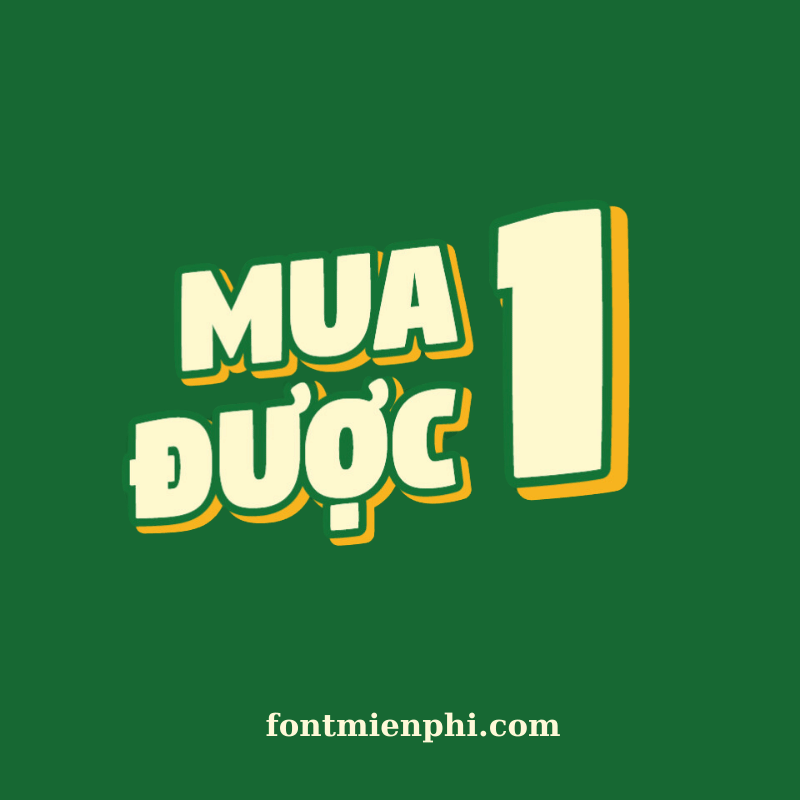
Font Việt hóa 1FTV VIP Digitalt
• Tác giả:  gluk
• Việt hóa:  fonttiengviet.com
Trong thế giới thiết kế đồ họa hiện đại, việc lựa chọn một bộ phông chữ phù hợp đóng vai trò quyết định đến tính thẩm mỹ và sự chuyên nghiệp của sản phẩm. Một trong những lựa chọn hàng đầu hiện nay chính là Font Việt hóa 1FTV VIP Digitalt. Đây là bộ Font Miễn Phí được tinh chỉnh kỹ lưỡng nhằm mang lại trải nghiệm tốt nhất cho người dùng Việt Nam, đặc biệt là trong các dự án đòi hỏi sự hiện đại và sắc nét.
Đặc điểm nổi bật của Font Việt hóa 1FTV VIP Digitalt
Bộ phông chữ này gây ấn tượng mạnh nhờ phong cách Digital hiện đại với các đường nét hình học vuông vức nhưng vẫn giữ được độ thanh thoát cần thiết. Phiên bản Font Việt hóa 1FTV VIP Digitalt đã được khắc phục hoàn toàn lỗi hiển thị dấu tiếng Việt, giúp các nhà thiết kế tự do sáng tạo mà không lo lắng về các ký tự bị lỗi font hay thiếu dấu cơ bản.
Tính ứng dụng cao trong học đường và đời sống
Với phong cách trẻ trung, bộ chữ này rất phù hợp để làm slide thuyết trình, tiêu đề báo tường hoặc các bảng tin trường học. Sự rõ ràng của Font Việt hóa 1FTV VIP Digitalt giúp học sinh và giáo viên dễ dàng truyền đạt thông điệp một cách trực quan nhất. Ngoài ra, nó còn được ứng dụng rộng rãi trong thiết kế logo, banner website và các ấn phẩm quảng cáo công nghệ cao.
Lợi ích khi sử dụng Font Việt hóa 1FTV VIP Digitalt